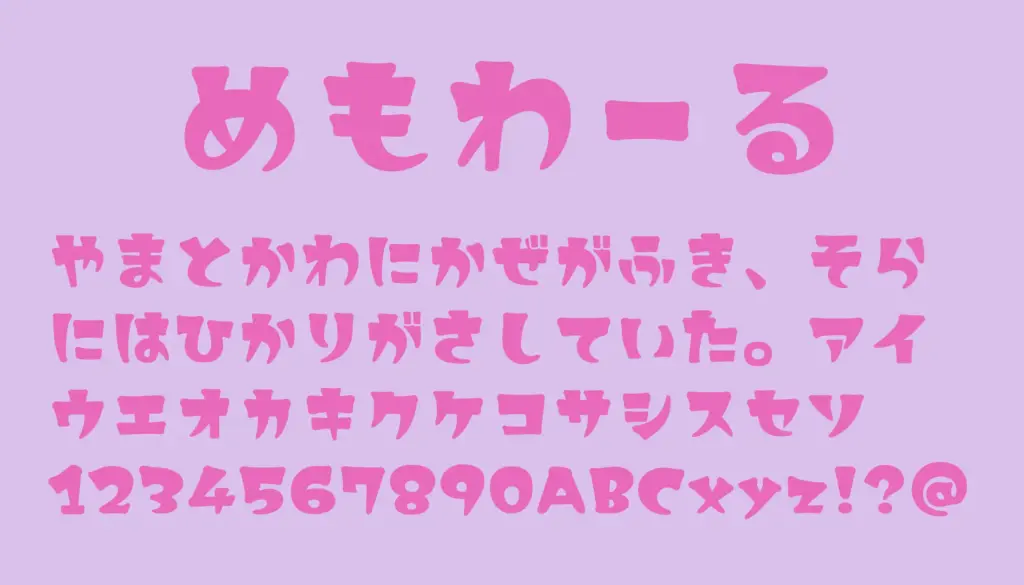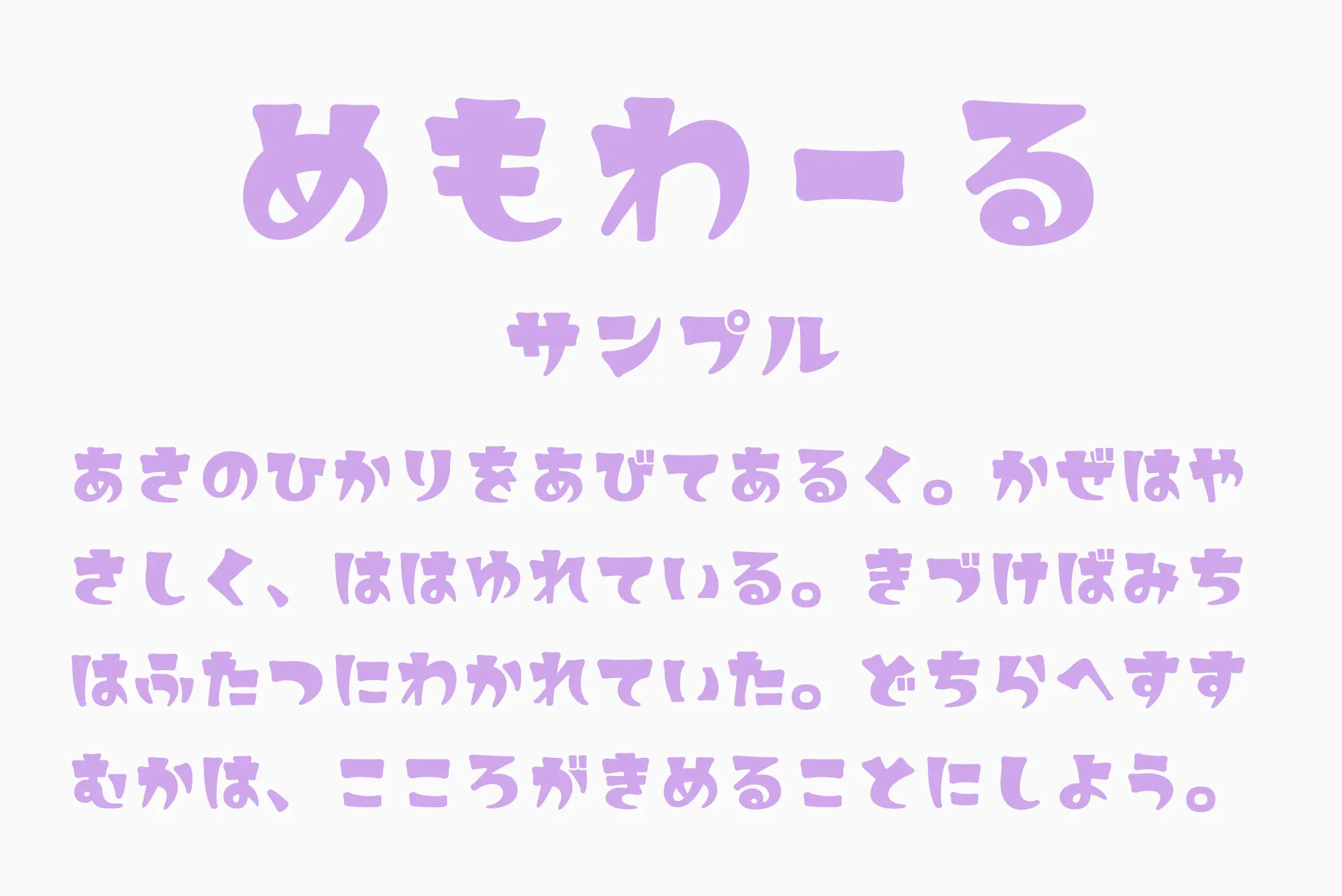
レトロでポップな雰囲気が魅力のひらがな・カタカナ専用フリーフォントです。ファンシー雑貨や昭和の広告を思わせるような、やや懐かしさを感じさせるデザインで、見出しやタイトルなどにぴったり。バリエーションとして、シャープな印象の「しかく」と、やわらかい印象の「まる」も用意されており、用途に応じて使い分けが可能です。
めもわーる